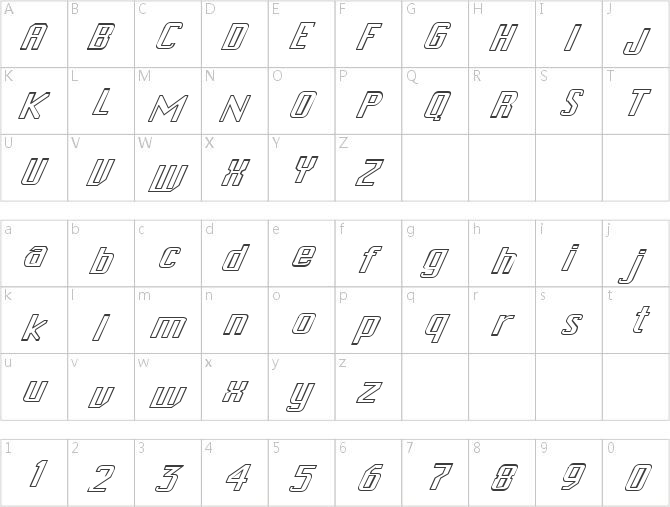
FZ BASIC 46 HOLLOW ITALIC 詳情頁
FZ BASIC 46 HOLLOW ITALIC字體字庫是一款讓人賞心悅目、百看不厭的英文字體,適合各類廣告和產(chǎn)品包裝設(shè)計應(yīng)用,字體大小0.1MB,格式為ttf字體,上傳用戶是白刃寒走得慢,作者/版權(quán)方為未知